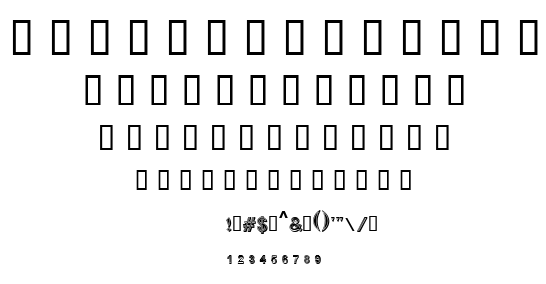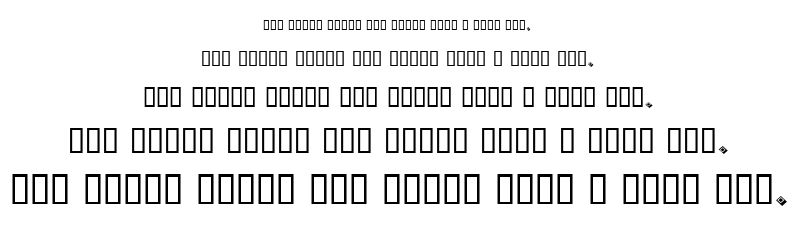
مراد بطرس Font
8 أوزان من خط BOUTROS ADS PRO من مجموعة خطوط المصمم مراد بطرس صممت هذه الخطوط ما بين الأعوام 1997 و 2001 وتم نشرها للاستخدام المجاني الشخصي من خلال شركة أدوبي حيث أرفقت هذه الخطوط ضمن قرص برنامج Adobe Photoshop 7 النسخة الأصلية عام 2003 م – تعمل هذه الخطوط على برامج أدوبي وأوفيس و كوريل .تظهر هذه الخطوط مرتبة ببادئة BOUTROS ADS PRO في قائمة الخطوط العربية . هذه النسخة من الخطوط تصلح للنظامين ويندوز و ماكنتوش، وتحوي باقة رائعة من خطوط العنونة والنص وجديرة بالإقتناء .